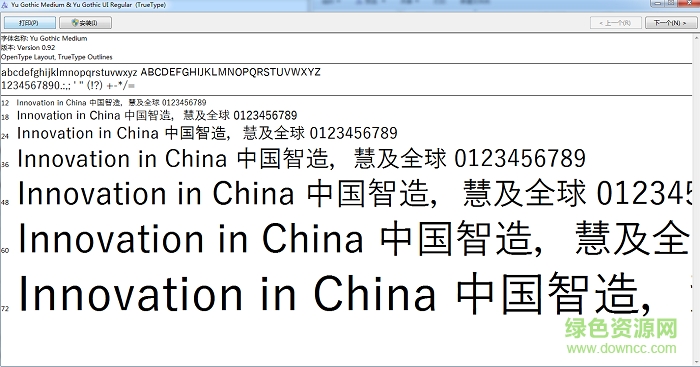
yu gothic medium字體是一款方整精致的英文字體,形態(tài)端正,斜正相倚,可以廣泛應(yīng)用于名片招牌設(shè)計(jì)、平面設(shè)計(jì)、排版印刷等領(lǐng)域,下載即可使用,需要的小伙伴快來下載收藏吧!
yu gothic兼具襯線字體的飽滿和非襯線字體的醒目,用來做PPT比較合適,一般來說,主要用作正文字體。